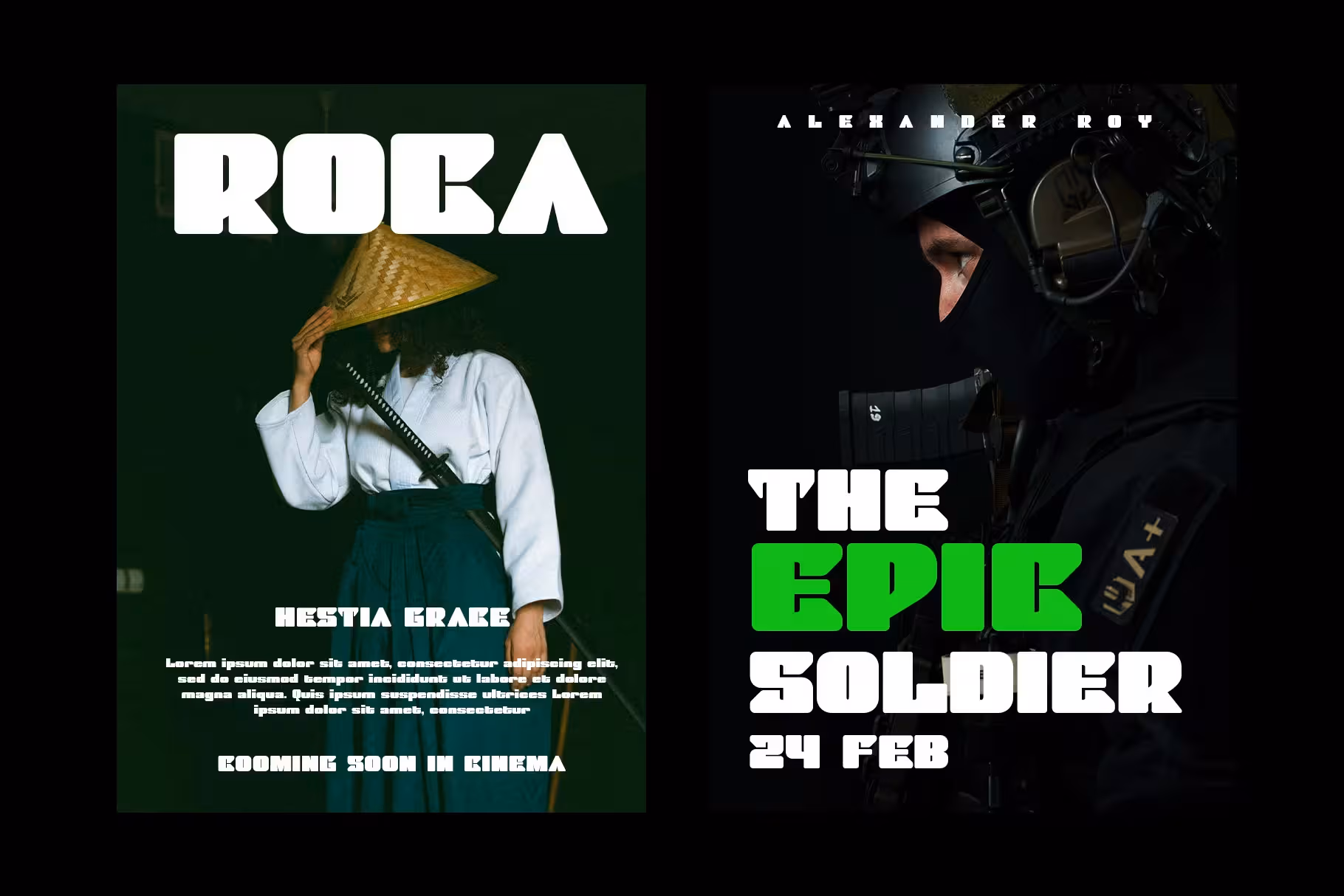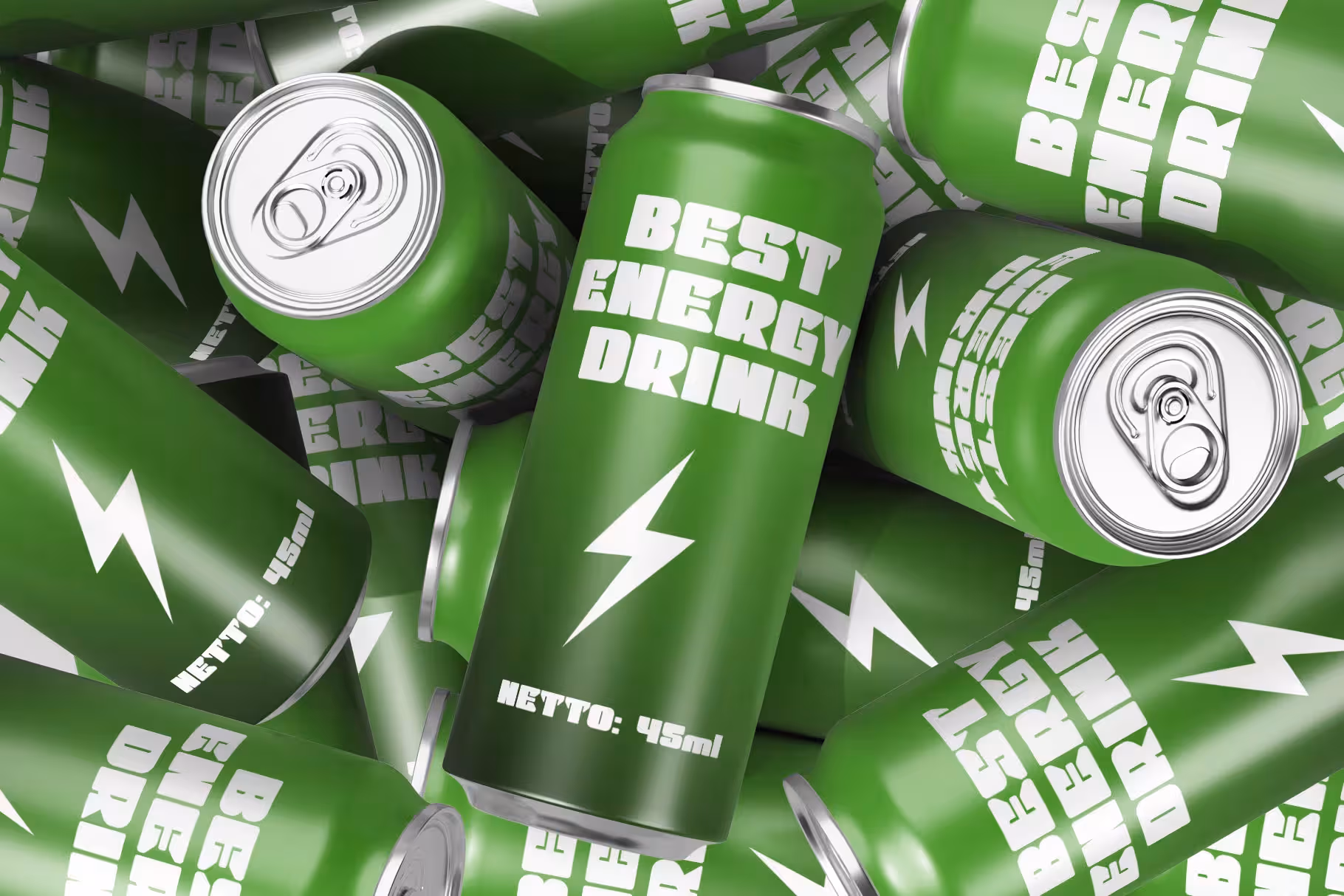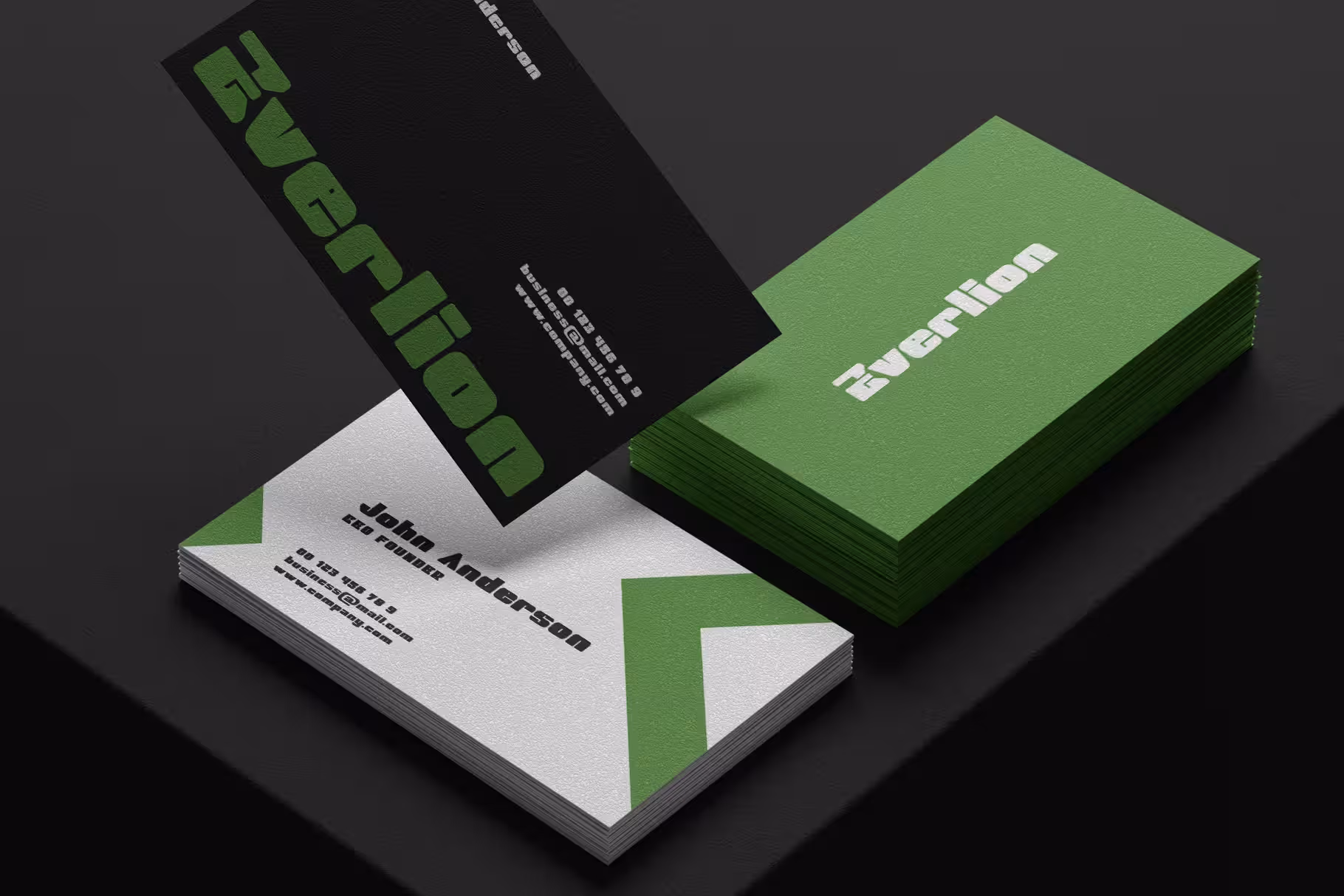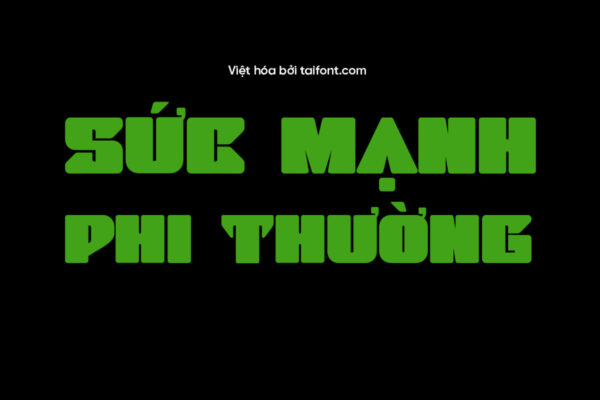
Giới thiệu về Font TF Stenar Việt hóa
TF Stenar Việt hóa là một font chữ trang trí nổi bật với thiết kế to lớn, mạnh mẽ và đầy ấn tượng, lý tưởng để truyền tải sự năng động, kịch tính và một phong thái hiện đại, dứt khoát. Font này toát lên vẻ vững chãi, tốc độ và đầy cá tính, phù hợp để tạo điểm nhấn nổi bật và thu hút mọi ánh nhìn, đặc biệt trong các lĩnh vực giải trí và thể thao.
Với đặc điểm là kích thước lớn, độ dày ấn tượng và khả năng tạo ấn tượng thị giác mạnh mẽ, Stenar là lựa chọn hoàn hảo cho các thiết kế muốn truyền tải sự nổi bật và phong cách:
- Poster thể thao: Hoàn hảo cho các poster, banner quảng bá giải đấu thể thao, sự kiện thể hình, hoặc các thương hiệu liên quan đến vận động. Font này giúp tạo không khí sôi động, cạnh tranh và mạnh mẽ, thúc đẩy tinh thần chiến thắng và gây ấn tượng thị giác mạnh mẽ.
- Thiết kế game: Lý tưởng cho logo game, tiêu đề, hoặc các ấn phẩm quảng bá các tựa game hành động, phiêu lưu, hoặc khoa học viễn tưởng. Nét chữ to lớn, dứt khoát của Stenar sẽ làm tăng tính kịch tính và độ “ngầu” cho trò chơi.
- Film ảnh hành động: Phù hợp cho các tiêu đề phim, poster phim, hoặc các đoạn giới thiệu cho thể loại phim hành động, phiêu lưu, hoặc khoa học viễn tưởng. Font này giúp tạo không khí mạnh mẽ, đầy sức hút và gây tò mò cho người xem.
- In ấn và quảng cáo: Đảm bảo khả năng đọc tốt ngay cả ở kích thước lớn, và tạo hiệu ứng thị giác mạnh mẽ khi in trên các chất liệu khác nhau như bảng hiệu, backdrop sự kiện hoặc các ấn phẩm quảng cáo.
Với TF Stenar Việt hóa, bạn có thể dễ dàng thổi hồn mạnh mẽ, năng lượng và sự độc đáo vào các thiết kế, tạo ra những sản phẩm không chỉ đẹp mắt mà còn cực kỳ ấn tượng và có khả năng thu hút sự chú ý tối đa.
Font Việt hóa TF Stenar